艺术字是极具特殊效果的一种文字风格,常常体现于广告、海报等艺术创作的美化效果。以强烈、醒目的视觉感受来达到创作意义。接下来给大家推荐的就是几款极具艺术特色的字体。
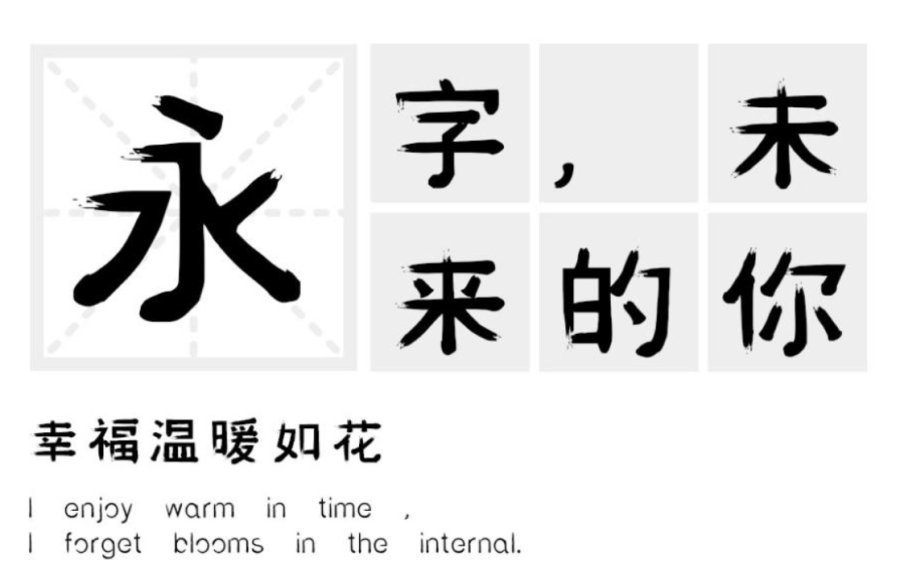
汉标颓废体:这款字体大量采用飞白风格,把笔画夸张化,从字体图片 可以看出桀骜不驯、永不服输的傲气,个性十足。运用弧形线条去表现随性的特征。适用于文艺类的书刊、品牌广告和产品包装设计,以及社交网络的个性化用字等方面。
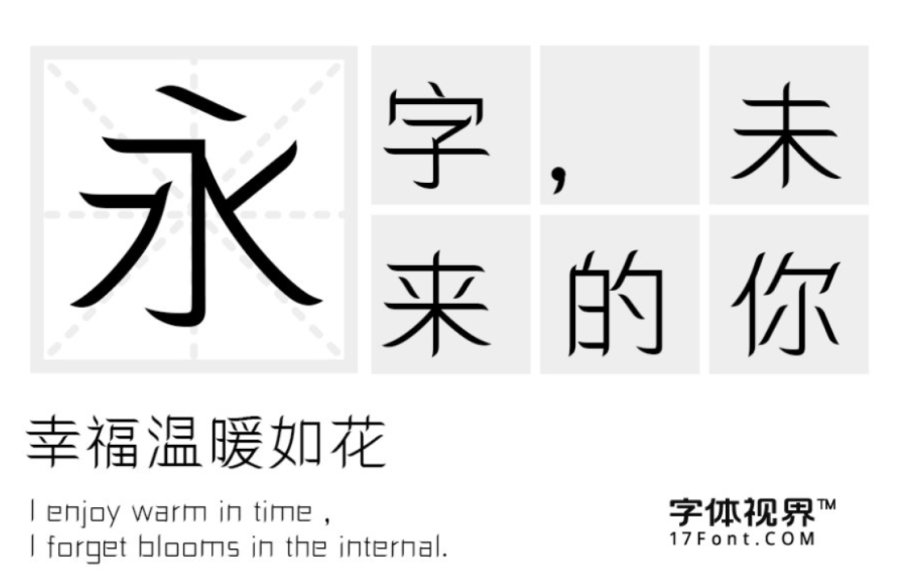
三极细柳简体:这款字体整体风格轻巧简洁,笔画飘逸、平直、粗细匀称。字体的灵感来源于柳叶,所谓弱柳扶风,江水出平。给人一种温暖亲切、婉约柔和的感觉。笔画转折明显,细节刻画干净利落。适用于封面设计、印刷、屏幕显示、广告等领域。
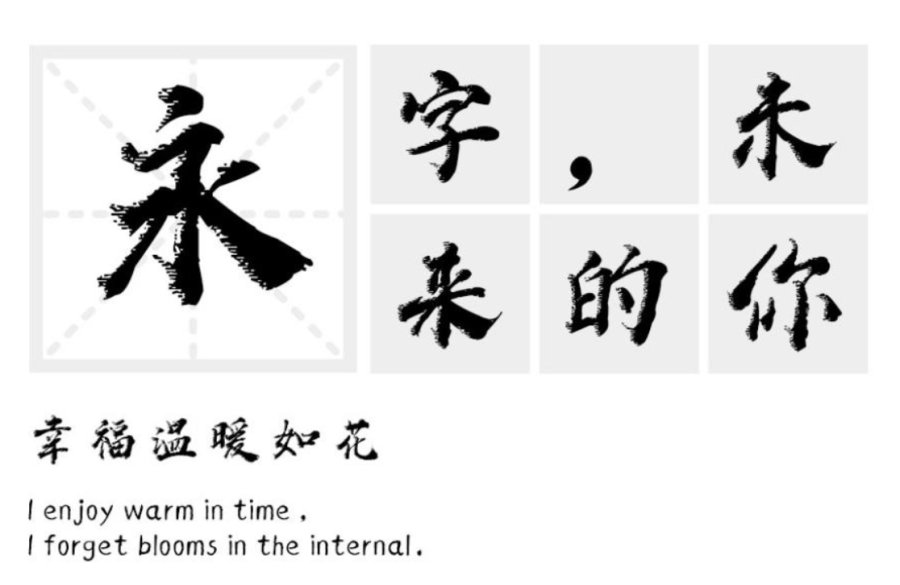
汉标赵苑蜡笔简体:这是一款既遒劲有力又不失文雅风韵的特色行体。延续了传统书法的特色 ,一笔一划都体现出沉着稳重、刚柔并济。蜡笔字样的风格又带有浓郁的艺术气息。适用于创意类设计、封面标题、屏幕显示、等领域。
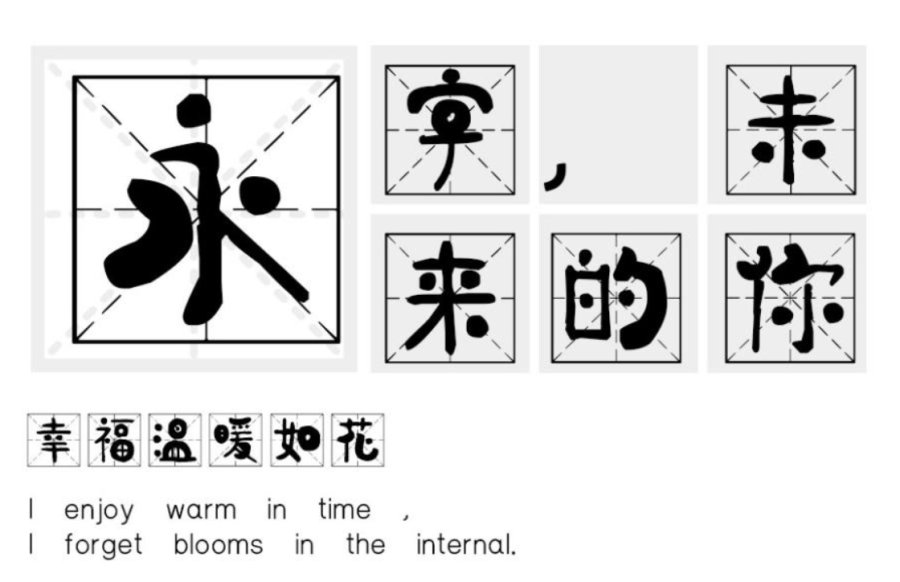
汉标燕赵米格体:米格在配上童趣稚气的字体风格,仿佛回到了学生时代。笔画简约、粗中有细。适用于少儿识别字体类、文艺类的书刊、品牌广告、产品包装设计,以及社交网络的个性化用字等领域。